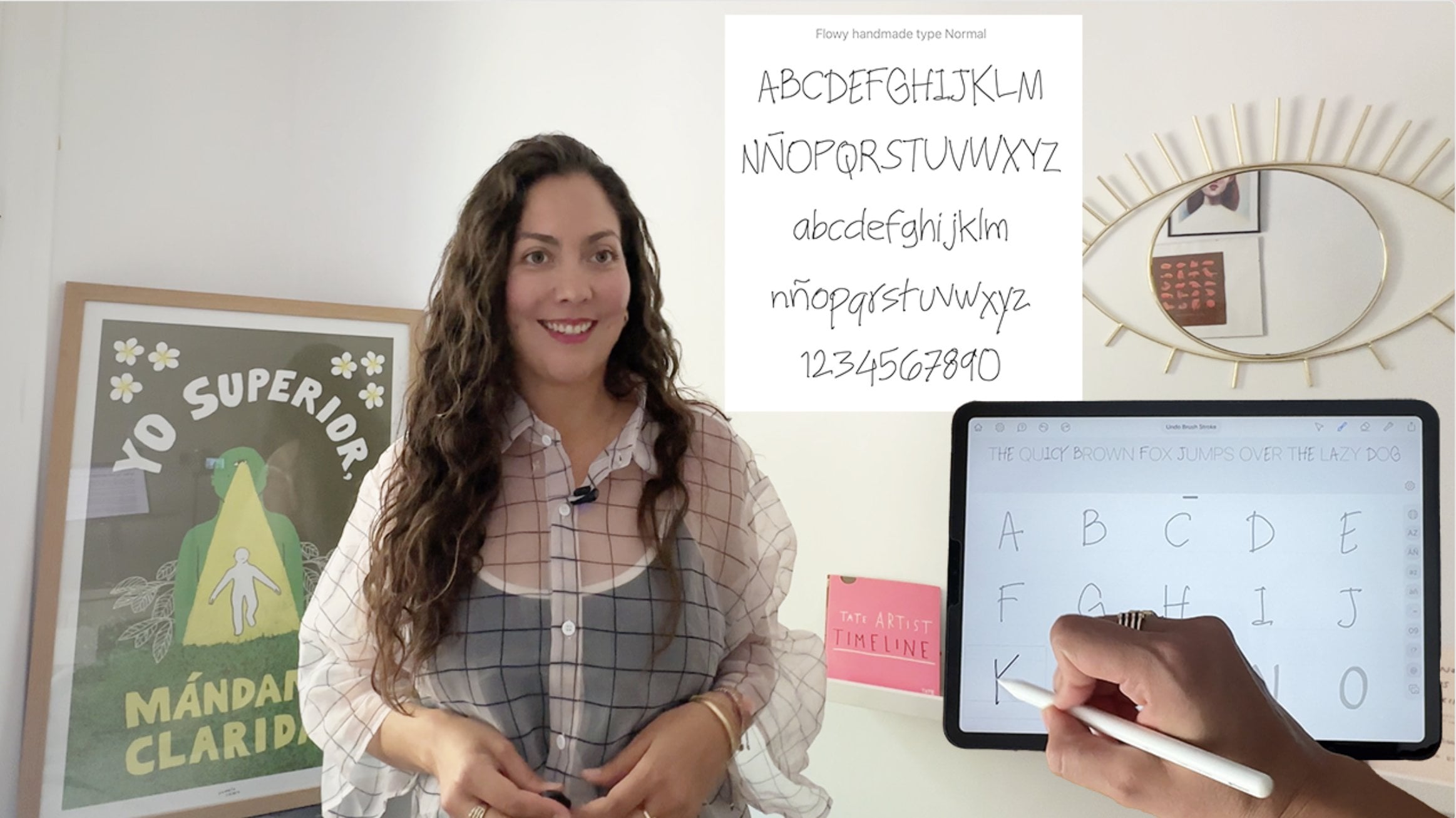
Erstellen Sie Ihre eigene Schriftart: Verwandeln Sie Ihre Handschrift in eine herunterladbare Schriftart | Pamela Calero | Skillshare
Erstellen Sie Ihre eigene Schriftart: Verwandeln Sie Ihre Handschrift in eine herunterladbare Schriftart
In einer digitalen Welt, in der Menschen zunehmend dieselben Vorlagen, Schriftarten und KI-generierten visuellen Elemente verwenden, wird handgefertigter Ausdruck wertvoller denn je. Warum also nicht eine Schriftart erstellen, die wie alle anderen klingt, anstatt dieselben Schriftarten wie Sie?
Durch das Erstellen einer eigenen Schriftart können Sie Ihre Arbeit wieder mit menschlichem Touch verbinden.
Hallo! Mein Name ist Pamela Calero, ich bin Creative Director und visuelle Geschichtenerzählerin. Ich formuliere Ideen visuell, um zielgerichtete Projekte durch einen poetischen und konzeptionellen Ansatz zu vereinfachen.
Als jemand, der Authentizität in der visuellen Kommunikation sehr schätzt, war ich schon immer fasziniert von Typografie und der emotionalen Kraft der Handschrift. Eine handgemachte Schrift kann Wärme, Intimität, Verspieltheit, Unvollkommenheit, Spontaneität und Charakter auf eine Weise vermitteln, die digitale Standardschriftarten einfach nicht können.
Ganz gleich, ob Sie eine Marke für sich selbst aufbauen, Arbeiten für einen Kunden erstellen oder digitale Grafiken erstellen: Individuelle Typografie macht sofort einen Unterschied. Es verwandelt Ihre visuelle Kommunikation in etwas Wiedererkennbares und Persönliches.
Handgemachte Lettering machen unglaublich viel Spaß, aber die Wahrheit ist, dass wir nicht immer die Zeit haben, alles jedes Mal von Grund auf neu zu erstellen. Die Umwandlung Ihrer Handschrift in eine Schriftart ist ein einmaliger Prozess, der Ihnen ein kreatives Werkzeug bietet, das Sie endlos wiederverwenden können.
Das Lustige daran ist, dass ich mich früher von Schriftarten-Software völlig eingeschüchtert fühlte. Es schien immer zu technisch und unzugänglich. Aber als ich Fontself entdeckte, öffnete sich mir eine ganz neue Welt kreativer Möglichkeiten.
In diesem Kurs zeige ich Ihnen eine einfache und verständliche Methode, wie Sie Ihre Handschrift in eine voll funktionsfähige Schriftart verwandeln können, die Sie auf Ihrem Computer installieren und verwenden können.
Wir gehen folgendes durch:
• Wie Sie Ihre handschriftlichen Briefe vorbereiten
• So importieren Sie sie in Fontself
• So passen Sie den Abstand an und testen Sie Ihre Schriftart
• So exportieren und installieren Sie Ihre Schriftart
• Und wie Sie es in Ihren kreativen Projekten verwenden können
Sie können also so viele handgemachte Schriftarten erstellen, wie Sie möchten.
Dieser Kurs eignet sich perfekt für Designer, Illustratoren, Content-Ersteller, kreative Unternehmer oder alle, die ihrer visuellen Sprache eine persönlichere und authentischere Note verleihen möchten.
Vorkenntnisse in Typografie sind nicht erforderlich.
Am Ende dieses Kurses verfügen Sie über eine eigene herunterladbare Schriftart und ein neues Tool, mit dem sich Ihre Arbeit menschlicher, ausdrucksvoller und unverwechselbar individueller anfühlt.
Schnapp dir also einen Stift, deinen Lieblingspinsel oder dein iPad, und lass uns deine Handschrift in etwas verwandeln, mit dem du tatsächlich schreiben kannst.
Wir sehen uns im Kurs!
Pamela Calero
Creative Director and Visual Artist
Hello!
My name is Pamela Calero and I’m a Colombian born - Barcelona based Communication Artist & Visual Storyteller. I give visual form to ideas to simplify projects that think outside the box.
1. Einführung: Erstellen Sie Ihre eigene Schriftart: In einer digitalen Welt, in der sich Menschen zunehmend auf dieselben Vorlagen, Schriften, generierten KI-Bilder und ausgearbeiteten Ausdruck verlassen , wird das wertvoller denn je. Anstatt also die gleichen Schriften wie alle anderen zu verwenden, warum nicht eine erstellen , die nach dir klingt? Hallo. Ich bin Pamela Calero und ich bin Kreativdirektorin und bildende Künstlerin als jemand, der Authentizität und visuelle Kommunikation sehr schätzt Authentizität und visuelle Ich war schon immer fasziniert von Typografie und der emotionalen Kraft der Handschrift Eine handgefertigte Schrift kann Wärme, Intimität, Verspieltheit, Unvollkommenheit, Spontanität und Charakter auf eine Weise vermitteln , die Wärme, Intimität, Verspieltheit, Unvollkommenheit, Spontanität und Charakter auf eine Weise vermitteln, die herkömmliche digitale Schriften einfach nicht können. Ganz gleich, ob Sie für einen Kunden eine Marke aufbauen oder digitale Kunstwerke erstellen, die Typografie von Kostümen schafft sofort einen Unterschied Kostümen Sie verwandelt Ihre visuelle Kommunikation in etwas Wiedererkennbares und Persönliches Handlettering zu machen macht unglaublich viel Spaß. Aber die Wahrheit ist, dass wir nicht immer die Zeit haben , alles von Grund auf neu zu erstellen Ihre Handschrift in eine Schrift umzuwandeln , ist ein einmaliger Prozess, der Ihnen ein kreatives Werkzeug an die Hand gibt, das Sie endlos verwenden können Das Lustige ist, dass ich mich früher von Typografie-Software einschüchtern ließ. Es schien mir immer zu technisch und unzugänglich. Aber als ich die Schrift selbst entdeckte, eine ganz neue Welt kreativer eröffnete sich mir eine ganz neue Welt kreativer Möglichkeiten Willkommen, um Ihre eigene Schrift zu erstellen. Verwandeln Sie Ihre Handschrift mit Fontself in eine herunterladbare Schrift In diesem Kurs zeige ich Ihnen, wie Sie einfache und leicht zugängliche Weise in eine Schrift umwandeln Ihre Handschrift auf einfache und leicht zugängliche Weise in eine Schrift umwandeln können, die Sie auf Ihrem Computer verwenden können Erfahren Sie, wie Sie Ihre handgeschriebenen Briefe vorbereiten, wie Sie den Schmerz anpassen und Ihre Schrift testen, wie Sie Ihre Schrift exportieren und auf Ihrem Computer installieren und wie Sie sie in Ihren kreativen Projekten verwenden können Sie können also so viele Schriften erstellen, wie Sie möchten. Dieser Kurs ist perfekt für Designer, Illustratoren, Inhaltsersteller, Unternehmer oder alle, die eine persönlichere und authentischere Note verleihen ihrer Bildsprache eine persönlichere und authentischere Note verleihen möchten Am Ende dieses Kurses verfügen Sie über Ihre eigene herunterladbare Schrift und ein neues Tool, mit dem sich Ihre Arbeit menschlicher und unverkennbarer anfühlt menschlicher und unverkennbarer Schnappen Sie sich also Ihr iPad und lassen Sie uns Ihre Handschrift in etwas verwandeln, mit dem Sie tatsächlich tippen können. Wir sehen uns im Unterricht 2. Kurs-Projekt:: Klassenprojekt, Sie werden mit Fontself Ihre eigene benutzerdefinierte handgeschriebene Schrift erstellen Fontself Ihre eigene benutzerdefinierte handgeschriebene Schrift erstellen Sie benötigen die Fontself-App für das iPad, ein iPad und einen Apple Pencil oder einen ähnlichen Stift sowie einen Computer, auf dem Sie Ihre Schrift installieren können Das Ziel ist nicht Perfektion, es ist Persönlichkeit. In diesem Kurs erfahren Sie, wie Sie ein zusammenhängendes handgeschriebenes Alphabet erstellen, Sie Ihre Schrift lesbar und ausdrucksstark machen können, Abstände und Zeichenplatzierung anpassen, eine Schriftdatei exportieren, Ihre Schrift auf Ihrem Computer installieren und Ihre Schrift in einer echten kreativen Anwendung verwenden Denken Sie daran, dass Ihre Handschrift bereits einen visuellen Ton enthält In diesem Kurs geht es darum, diese Stimme in ein kreatives Tool zu verwandeln , das Sie weiterhin für Ihr Branding, Ihre Kunstwerke, Ihre sozialen Medien, Präsentationen oder kreativen Projekte verwenden Ihre Kunstwerke, Ihre sozialen Medien, Präsentationen oder kreativen Projekte Erstelle deine eigene handgeschriebene Schrift und teile einen Screenshot eines damit geschriebenen Satzes Sie können auch Screenshots Ihres Prozesses in der Fontself-App teilen Screenshots Ihres Prozesses in der Fontself-App 3. Installation der Fontself-App: In diesem Kurs werden wir die native iPad-Version der App verwenden die native iPad-Version der App Fontself hat zwar eine Desktop-Version für Illustrator oder Photoshop Die iPad-App ist bei weitem der einfachste und schnellste Weg , um eigene Schriften zu erstellen Nun, es gibt derzeit keine native Android-Version von Fontself Wenn Sie ein Android-Tablet verwenden, empfehle ich Ihnen, Alternativen wie Fonte zu erkunden Der Prozess wird sehr wahrscheinlich ähnlich sein. Fontself ist eine kostenpflichtige App, aber es ist ein einmaliger Kauf, und die Investition lohnt sich absolut, wenn Sie handgemachte Typografie mögen oder benutzerdefinierte Schriften für Ihre Arbeit erstellen möchten benutzerdefinierte Schriften für Ihre Arbeit erstellen Sobald Sie die App heruntergeladen haben, wird sie automatisch auf Ihrem iPad installiert 4. Erstellen Ihrer Schriftart: Fahren Sie fort und öffnen Sie die Fontself-App. Sie werden feststellen, dass die Schriftarten, die ich zuvor erstellt habe , in der MyFonts-Bibliothek angezeigt werden Dies ist eine großartige Möglichkeit, all Ihre benutzerdefinierten Schriften an einem Ort im Auge zu behalten all Ihre benutzerdefinierten Schriften an einem Ort im Auge Die App führt verschiedene Vorlagenstile aus denen Sie wählen können, z. B. Hand-, Curl-, Script-, Gothic-, Graph-, Fett-, Sound Serif- oder sogar Vorlagen mit benutzerdefinierter für dieses Klassenprojekt mit einer Handvorlage beginnen, Lassen Sie uns für dieses Klassenprojekt mit einer Handvorlage beginnen, damit Sie Ihre Handschrift in eine Schrift umwandeln können Fahren Sie fort und klicken Sie darauf. Sie werden feststellen, dass eine Vorlage auf dem Bildschirm erscheint. Dies dient als Leitfaden, den Sie bei der Erstellung Ihrer Briefe nachvollziehen können . Sie werden auch zusätzliche Zeichen und Symbole bemerken. Diese sind besonders nützlich, wenn Sie vorhaben, in anderen Sprachen als Englisch zu schreiben , oder Sie eine vollständigere Schrift wünschen. Fehlt ein Zeichen, erscheint es bei der späteren Eingabe einfach leer Beachten Sie, wie Sie Pinselgröße, Rundheit, Druck, Winkel und Stiftrichtung anpassen können Rundheit, Druck, Winkel und Stiftrichtung Sie können auch zwischen Werkzeugen wie Stift, Bleistift, Marker, Feder oder Kalligraphiestift wechseln Bleistift, Marker, Feder oder Kalligraphiestift Ich strebe also lockere und unvollkommene Striche an. Wählen Sie das Tool , das am besten zu dem Gefühl passt , das Ihre Schrift vermitteln soll In meinem Fall möchte ich, dass sich die Schrift fließend und handgemacht anfühlt, fast wie ein Handlettering Machen Sie sich keine Sorgen, wenn Sie einen Fehler machen. Sie können jederzeit das Radiergummi verwenden, um einen Teil eines Buchstabens zu korrigieren oder ihn vollständig zu löschen Sie beim Vervollständigen Ihrer Buchstaben, Beachten Sie beim Vervollständigen Ihrer Buchstaben, wie der Satz oben automatisch ausgefüllt wird Der schnelle braune Fuchs, der über den faulen Hund springt , ist ein berühmtes Pangram, was bedeutet, dass es jeden Buchstaben des Alphabets mindestens einmal enthält des Alphabets mindestens einmal Diese Vorschau ist auch nützlich, um Buchstaben zu erkennen, die sich unangenehm anfühlen, wenn sie nahe beieinander oder seltsam angeordnet Sie können sie jederzeit nach Bedarf anpassen. Pattern. Muster. Und herzlichen Glückwunsch. Sie haben gerade Ihre erste Schrift erstellt. Und jetzt sind Sie bereit, sie zu exportieren. 5. Exportieren der Schriftart Installieren und Verwenden: Wir sind jetzt bereit, Ihre Schrift von Fontself auf Ihrem iPad auf Ihren Computer zu exportieren Fontself auf Ihrem iPad auf Ihren , damit Sie sie installieren können Fahren Sie fort und klicken Sie oben rechts auf die Schaltfläche Exportieren oben rechts auf die Klicken Sie dann auf Schriftdatei exportieren, und die App bereitet Ihre Schrift vor. Wenn Sie einen Mac-Computer verwenden, können Sie die Datei einfach über AirDrop übertragen Sie können es auch in Ihren Dateien speichern oder es per E-Mail an sich selbst senden, um es auf einem anderen Gerät oder Betriebssystem zu installieren , z. B. Windows oder Linux Sobald sich Ihre Schrift auf dem Computer befindet, doppelklicken Sie darauf. Es wird in Ihrem Schriftkatalog geöffnet. Klicken Sie auf Schriftart installieren und voila Ihre handgefertigte Schrift ist jetzt eine verwendbare Schrift auf Ihrem Computer Probieren Sie es in Apps wie Pages oder Word aus. Beachten Sie, dass einige Online-Plattformen Einschränkungen haben. Canva erlaubt beispielsweise Hochladen von benutzerdefinierten Schriftarten nur mit einer Pro-Version Und natürlich kannst du deine Schrift auch in der gesamten Adobe Suite verwenden Unabhängig davon, wo Sie sie verwenden, würde ich Ihre Schrift gerne in Aktion sehen Teile dein Lieblingszitat, Lieblingstext oder deine Lieblingsphrase, die mit deiner eigenen Schriftart geschrieben und im Klassenprojekt hochgeladen wurden 6. Fazit: Herzlichen Glückwunsch. Du hast es geschafft. Sie wissen jetzt, wie Sie Ihre Handschrift in eine funktionale Schrift verwandeln können, und können neue Schriften kreieren, die sich authentisch, ausdrucksstark und menschengemacht anfühlen , ausdrucksstark und menschengemacht Wenn dir dieser Kurs gefällt, lade dein Projekt bitte in die Klassengalerie Es spielt keine Rolle , ob deine Schrift fertig ist oder noch in Bearbeitung ist. Wo auch immer Sie sich befinden, ich würde mich freuen, Ihren Prozess zu sehen und Ihnen Feedback zu geben. Und wenn Ihnen dieser Kurs weitergeholfen hat, gerne eine Bewertung hinterlassen können Sie gerne eine Bewertung hinterlassen, damit mehr Menschen eine einfache und zugängliche Möglichkeit entdecken, ihre eigenen Schriften zu erstellen Vielen Dank, dass Sie zu mir gekommen Wir sehen uns beim nächsten Mal.